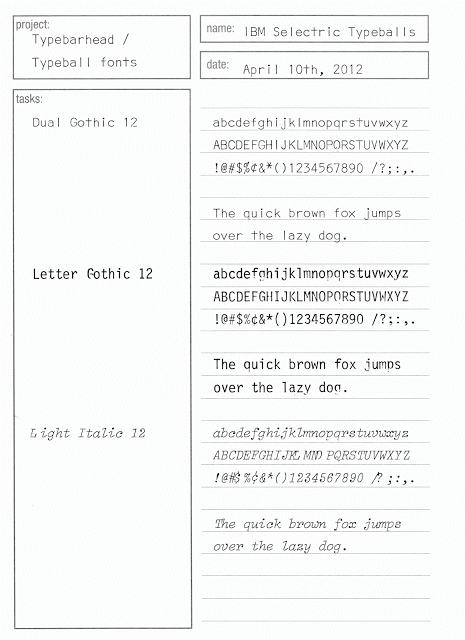
Typewriter-Kursive.
Hallo! Welche Schrift ist das? Man sieht eine recht gewöhnliche “Typewriter”-Schriftart, allerdings mit einer Kursive, die es mir angetan hat. Weiß jemand worum es sich handeln könnte?
(Gedruckt 1980 bei John Benjamins B. V.)
@Phoibos Freue mich über Deinen Hinweis. Leider gleichen die beiden Schriftarten sich nicht ganz, was man z. B. an der Form des kleinen “l” sieht. Ich habe mal hier ein Schaubild zum Vergleich angefügt.
Es gab auch für Fachliteratur, die in relativ kleinen Auflagen gedruckt wurde, immer wieder den Fall, daß das Werk überhaupt nicht gesetzt wurde, sondern mit Schreibmaschine geschrieben und optisch reproduziert. Das sieht mir hier eigentlich so aus, einige Indizien scheinen mir darauf hinzuweisen. Bei einem höher aufgelösten Scan könnte man das sicher genauer sagen. In dem Fall suchte man also eher nach einem Typenrad für eine elektronische Schreibmaschine, das eine Kursive mitbringt und eine Fette simuliert, indem der selbe Buchstabe mit geringem Horizontalversatz zweimal angeschlagen wird.